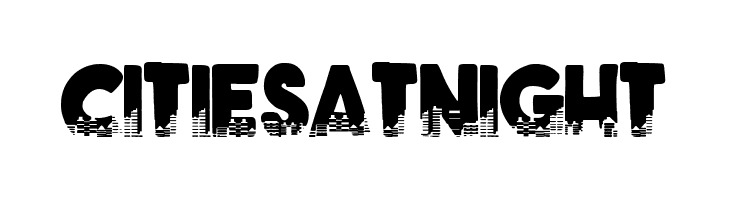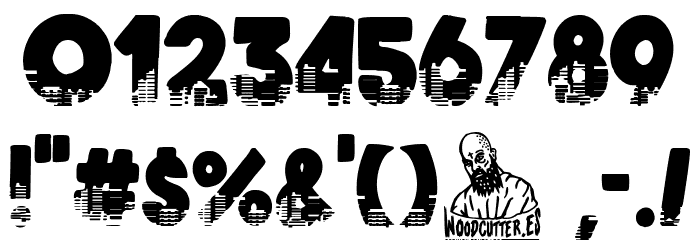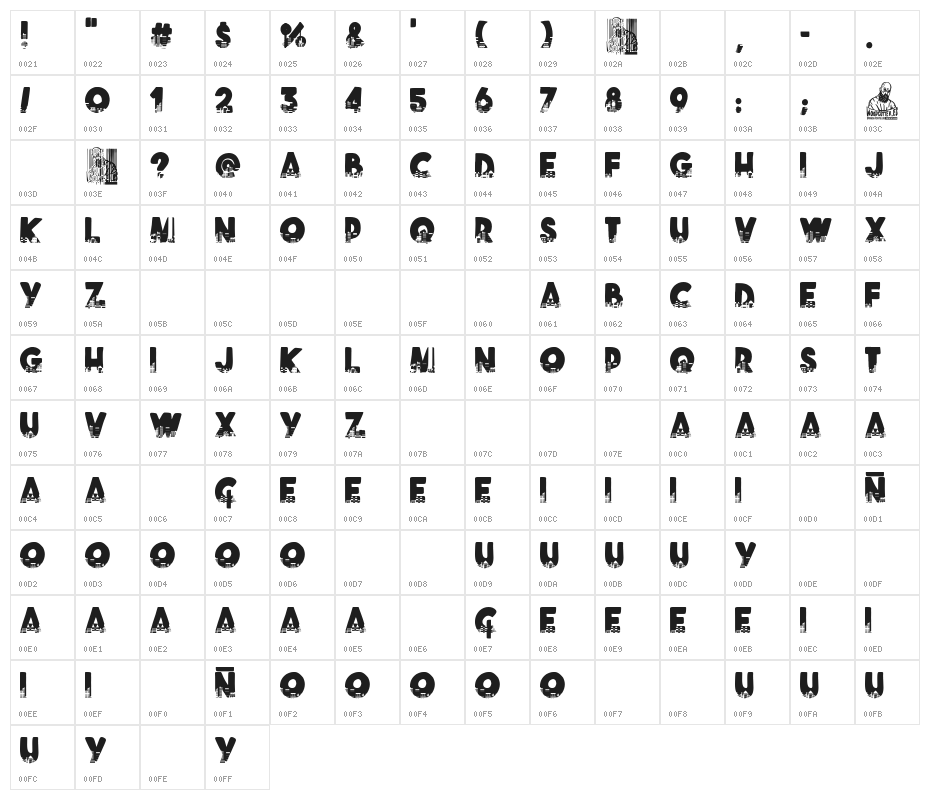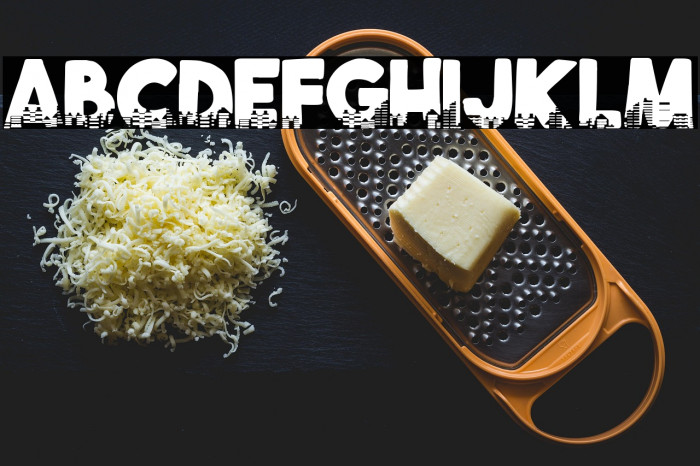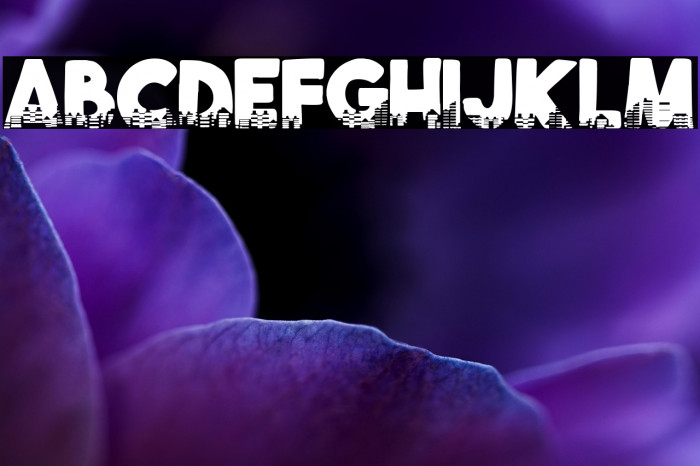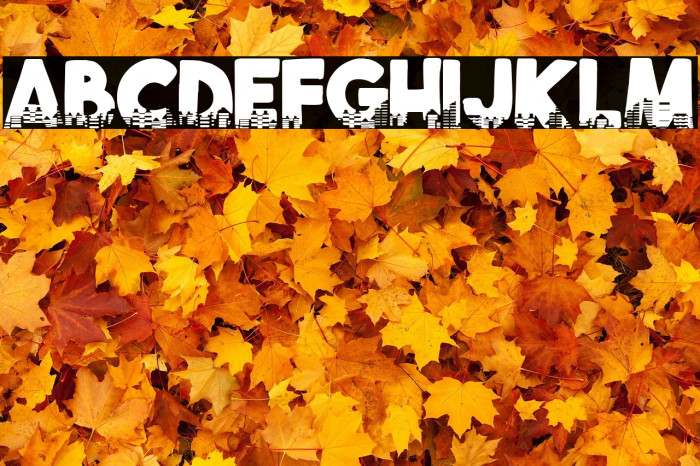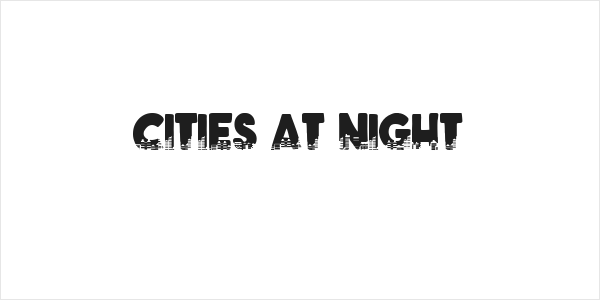
Cities at Night Font
| Estilo general | Modern, Decorative |
| Caso de uso | Headlines, Posters, Branding |
| Proyectos propuestos | Ideal for posters, headlines, branding, and any project needing a bold, urban aesthetic. |